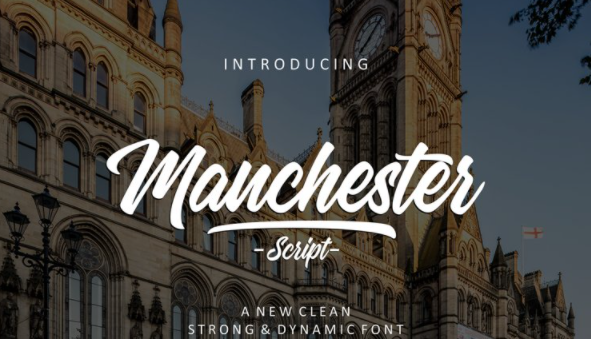
Название: Manchester Font (2021)
Manchester Script - это шрифт для рукописного ввода, обладающий очаровательной индивидуальностью. Этот шрифт также обладает большой подвижностью и чистотой. Вы можете использовать его для любых целей, таких как логотип, печатные цитаты, значок, знак отличия, упаковка, заголовок, плакат, футболка/аппликация, поздравительная открытка, приглашение на свадьбу и т.д.
Манчестерские шрифты доступны с множеством вариаций и бонусов. Состоит из прописных, строчных, цифровых, пунктуационных и многоязычных символов, а также включает некоторые функции OpenType, такие как лигатуры, стилистические альтернативные символы и штрихи.
Название: Manchester Font (2021)
Manchester Script - это шрифт для рукописного ввода, обладающий очаровательной индивидуальностью. Этот шрифт также обладает большой подвижностью и чистотой. Вы можете использовать его для любых целей, таких как логотип, печатные цитаты, значок, знак отличия, упаковка, заголовок, плакат, футболка/аппликация, поздравительная открытка, приглашение на свадьбу и т.д.
Манчестерские шрифты доступны с множеством вариаций и бонусов. Состоит из прописных, строчных, цифровых, пунктуационных и многоязычных символов, а также включает некоторые функции OpenType, такие как лигатуры, стилистические альтернативные символы и штрихи.